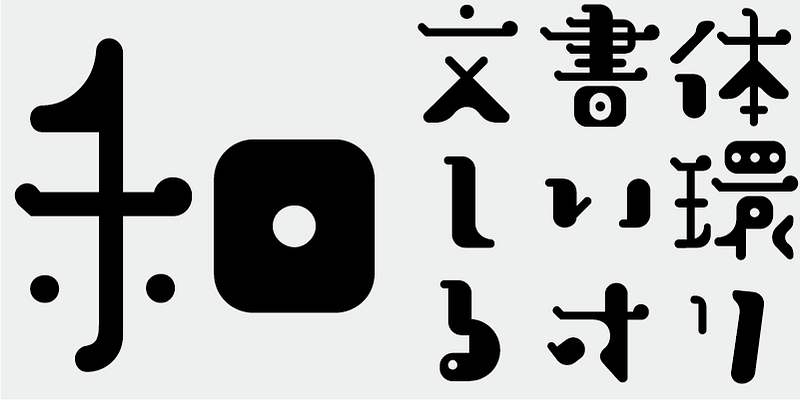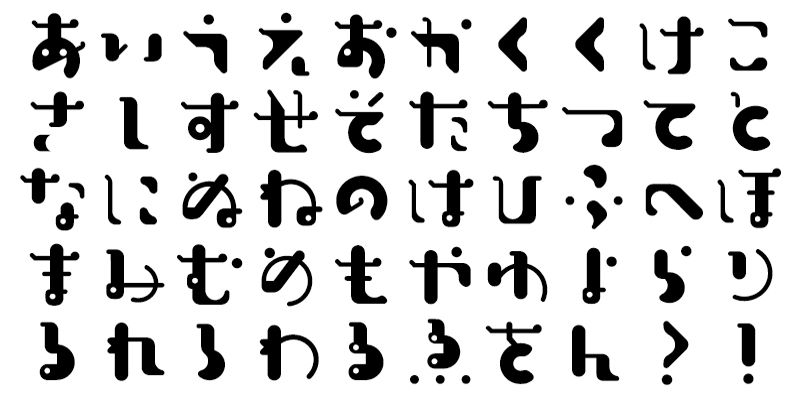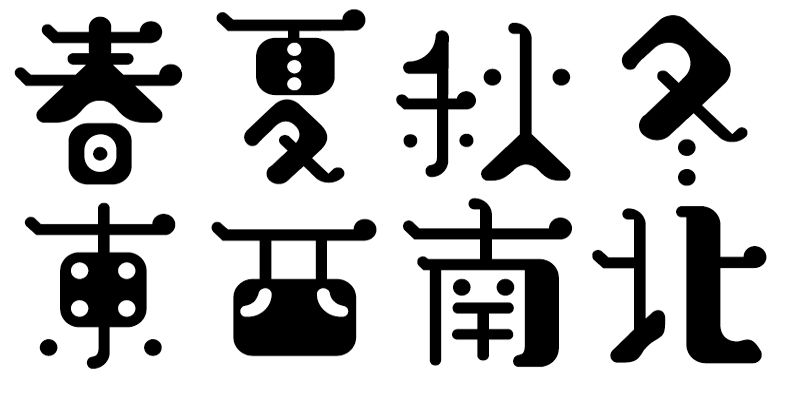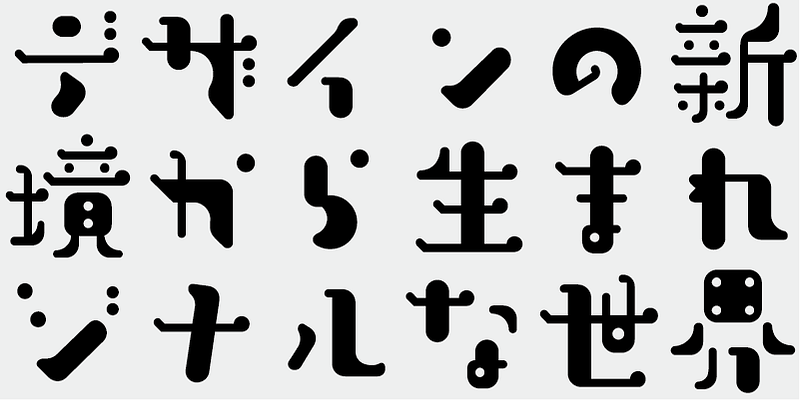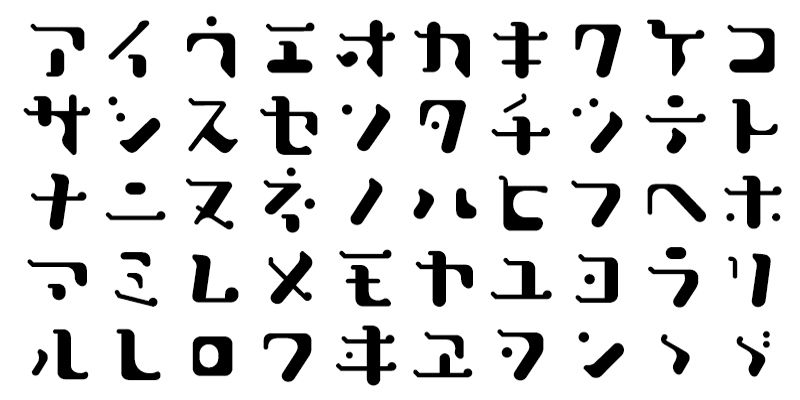
Aunque los caracteres tengan que ser legibles, esta tipografía se creó para retar esa noción con un diseño lo más agradable posible, como un conjunto de imágenes o símbolos.
Este tipo de letra incluye los mejores 1.000 caracteres kanji elegidos a partir de tablas de frecuencia de caracteres elaboradas por empresas periodísticas, editoriales e institutos de investigación lingüística, además de 206 caracteres kana y signos de puntuación.
En la producción de fuentes japonesas de hoy en día, los 7000 caracteres del estándar JIS se consideran esenciales. Pero, ¿todas las fuentes realmente necesitan 7000 caracteres? En la época de la fotocomposición, se necesitaban muchos menos caracteres. FONT1000, un grupo de diseñadores de tipos de letra independientes, comenzó con esa sencilla pregunta. Hemos seleccionado el mínimo de 1000 caracteres kanji (ideográficos) necesarios para la composición tipográfica en japonés y nos hemos esforzado en crear tipos de letra y fuentes de forma activa para admitirlos. Este conjunto de 1000 caracteres kanji se seleccionó utilizando datos de frecuencia de caracteres recopilados por empresas de periódicos, editoriales, organizaciones de investigación lingüística, etc., y también incluye caracteres silábicos kana y signos de puntuación. FONT1000 se formó en 2001 con 25 diseñadores y 25 tipos de letra. Hoy tenemos 130 tipos de letra y hemos crecido hasta incluir casi 40 miembros, lo que hace posible trabajar con tipos de letra con más caracteres.